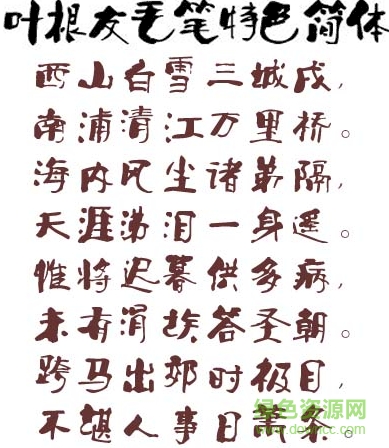
葉根友毛筆特色簡體是葉根友字庫中的一款特色簡體字體,這款字體結(jié)構(gòu)精簡,線條優(yōu)美,運(yùn)筆放縱,筆畫連綿,喜歡的朋友歡迎來綠色資源網(wǎng)免費(fèi)下載使用。
葉根友毛筆特色簡體是由中國書法奇人葉根友先生親自書寫的獨(dú)特創(chuàng)意的一款字體,該字體是一款具有獨(dú)特氣質(zhì)的毛筆書法字體,渾厚自然的筆畫,使書法與現(xiàn)代審美相結(jié)合,字形簡潔明了,筆畫有粗有細(xì),有正有奇,字型獨(dú)特創(chuàng)意。葉根友毛筆特色簡體特色明顯,打破傳統(tǒng)毛筆書法寫法,自創(chuàng)一派,用筆大膽而干練,在粗與細(xì)的對比中,體現(xiàn)了中國漢字千變?nèi)f化的特征。葉根友毛筆特色簡體擁有6763個中文漢字以及其他英文字母和阿拉伯?dāng)?shù)字,整體效果十分出眾,可以適用于名片設(shè)計(jì)、平面設(shè)計(jì)、廣告設(shè)計(jì)、報(bào)紙雜志、企業(yè)LOGO、商標(biāo)注冊、電視臺廣告等領(lǐng)域